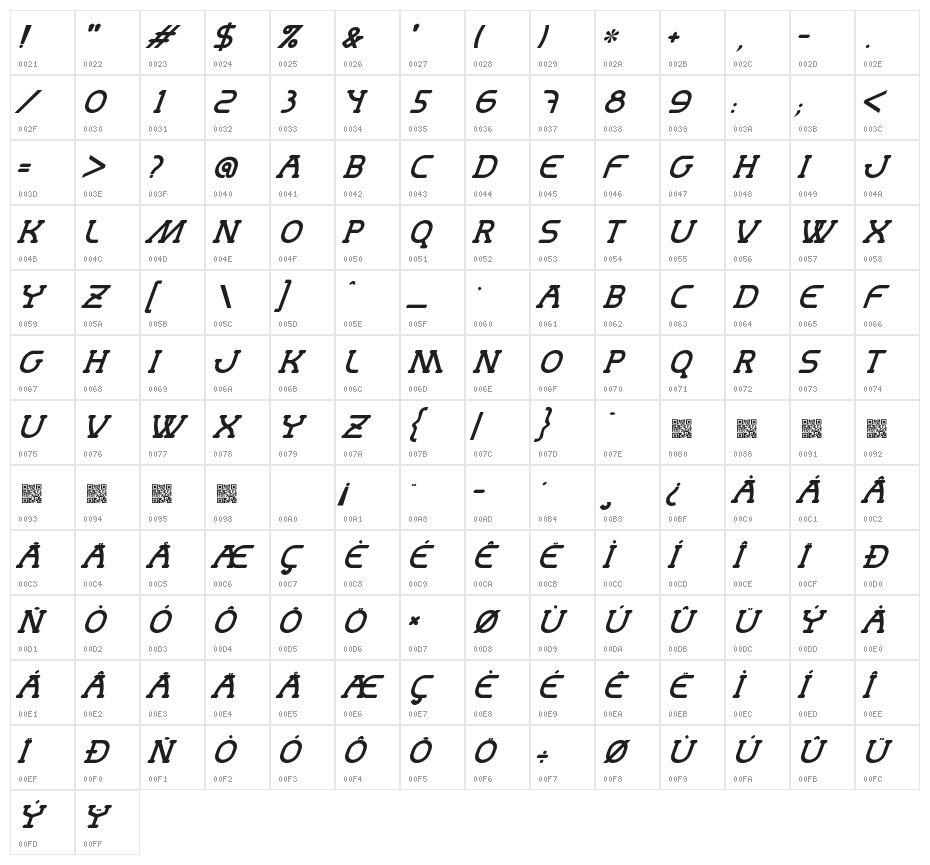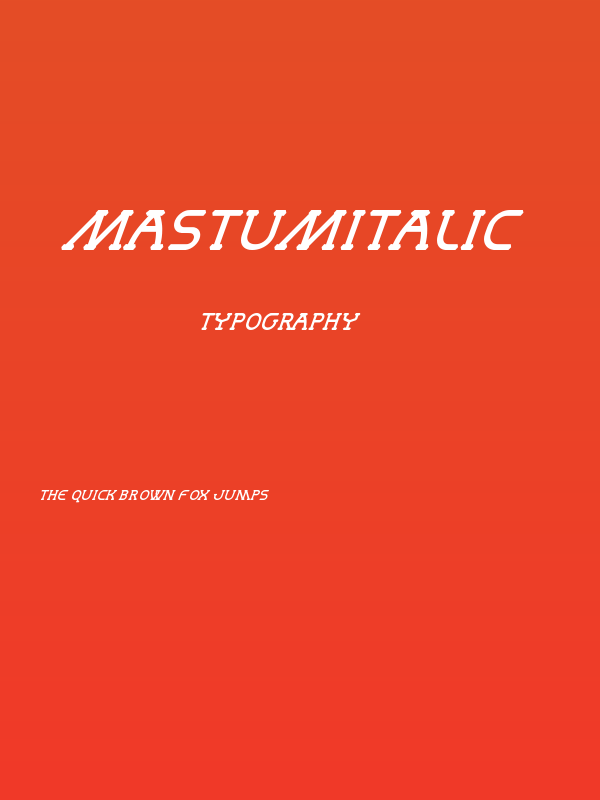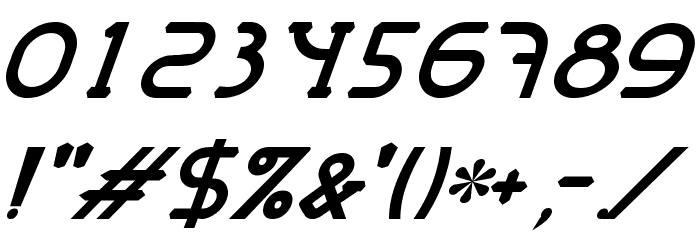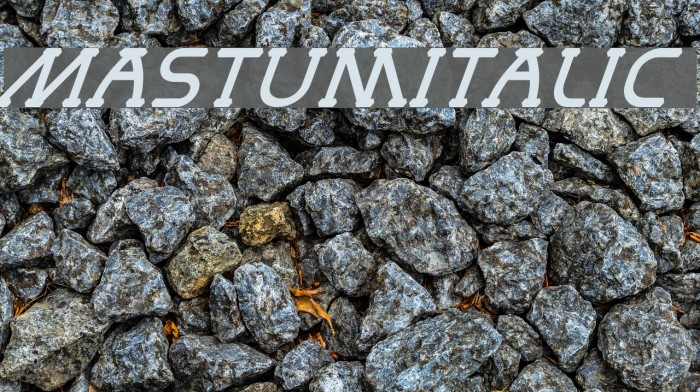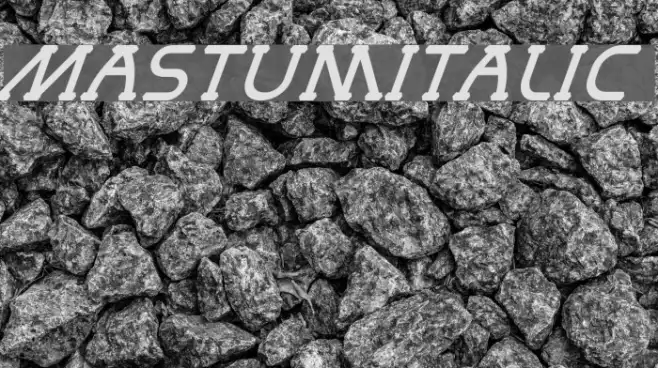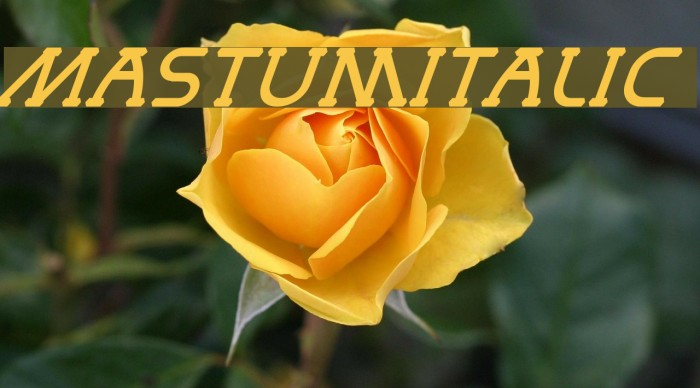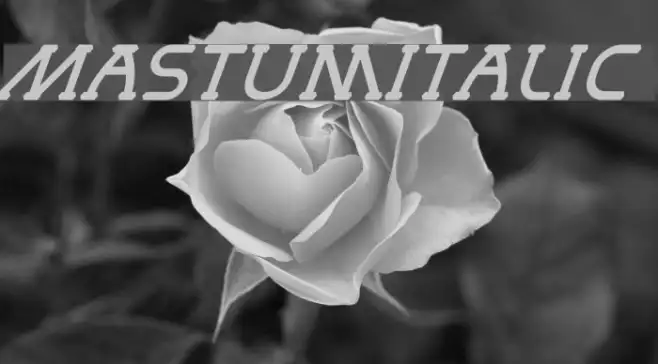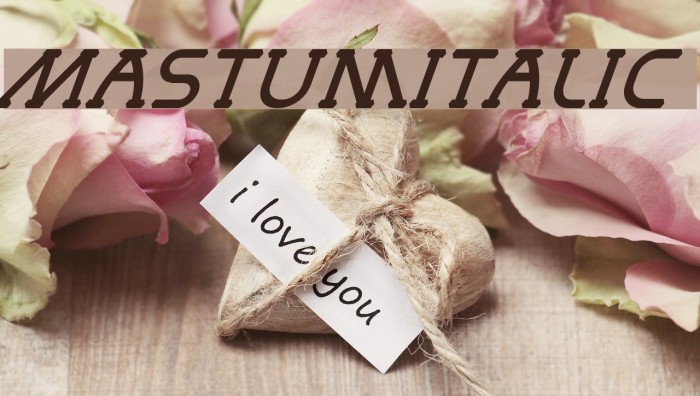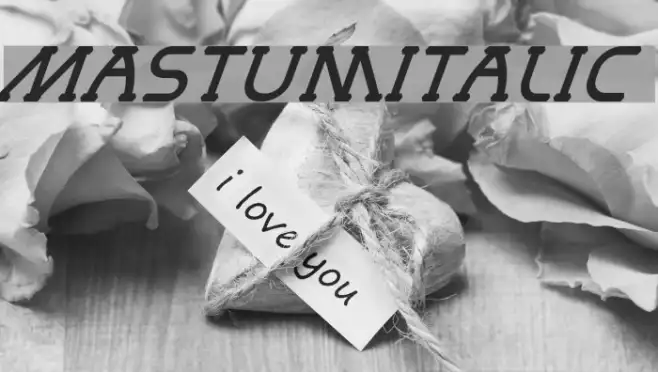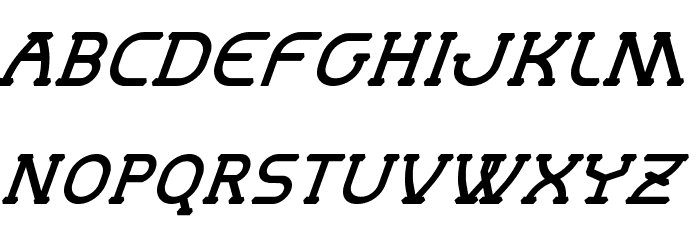
MastumItalic Font
| Proyectos propuestos | Ideal for branding, advertising, posters, and digital media where a modern and energetic look is desired. |